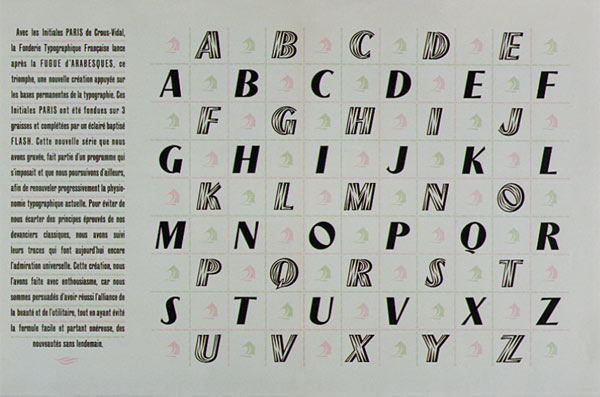
Crous-Vidal, un hombre entusiasta de su trabajo y autodidacta, no llegó al grafismo por los cauces habituales –el artista reconvertido en ilustrador por motivos económicos– sino porque creía profundamente en la importancia, modernidad y autonomía de la publicidad y la tipografía.
Artículo de la Revista Internacional de les Arts, tipografía y grabado en relieve, 1933-1934 (Izq.), cubierta Caractère, 1950 (dcha.)
El artista dedicó sus primeros años de trabajo a todo tipo de artes: cine, música, diseño, publicidad, pintura, literatura… Fue entonces, en 1933, cuando creó la revista Art, que debía haberse llamado Antiart, pero, debido a un error del fotograbador, cambió su cabecera definitivamente. En la revista participaban colaboradores de diferentes profesiones, todos ellos leridanos: arquitectos, filólogos, fotógrafos… y en sus páginas tenían cabida todos los aspectos relativos a la vanguardia: desde la danza o el cine sonoro, hasta la fotografía experimental, la iluminación o la arquitectura, todo siempre marcado por su fuerte espíritu combativo. En ella publicó sus poemas, artículos sobre publicidad letrística e imprenta y también diseñó sus cabeceras y titulares.
Díptico publicitario de Fugue d´Arabesques.
Tras la guerra civil, Crous-Vidal tuvo que exiliarse en Francia, donde comenzó su segunda etapa, en la que se aleja de los movimientos vanguardistas. A partir de ahora es cuando se consolida como diseñador gráfico y finalmente termina por dedicarse a la tipografía. Gracias a sus conocimientos sobre la imprenta, colaboró con la Resistencia en 1942 fabricando documentos falsos. En París trabajó tres años como maquetista de la prestigiosa imprenta Draeger y para diversas publicaciones del sector de la impresión y las artes gráficas. Fue en esta época cuando conoció a Maxilien Vox, editor de la revista Caractère, una importante publicación especializada donde dio a conocer sus letras. Vox que le animó a desarrollar su interés por la letrística en el terreno de la tipografía y a luchar por mantener un estilo arabesco y latino frente al poderío germano que reinaba en el período de entreguerras.
Anuncio del programa de Fiestas de Lleida, 1931-1932 (izq.), cubierta Caractère Noël, 1952 (dcha.)
Pero fue a partir de 1950, año en el que creó su propio estudio gráfico, cuando su obra alcanzó mayor fecundidad con un éxito fulgurante, debido a la firmeza y originalidad de sus propuestas. La Fonderie Typographique Française fundió su serie de viñetas Fuga de arabescos, que más tarde serían producidas por la Fundición Tipográfica Nacional.
Anuncio del programa de Fiestas de Lleida, 1931-1932.
Estas fueron concebidas por Crous-Vidal como el punto de partida de una investigación sobre motivos decorativos que aplicó a la tipografía, a la creación de papeles, tejidos y envases. Un año después diseñó las iniciales París, en tres grosores y sin caja baja, que tendrían difusión en Francia y España. Le seguiría la letra Flash tridimensional, una versión más hueca y más gruesa del carácter, que buscaba efectos ópticos y de relieve. Crous-Vidal continuará diseñando letras, como la Illerda o Ille de Francia, hasta que en 1966 consiguió registrar 26 patentes tipográficas.
Anuncio de Cinzano, 1947-1954.